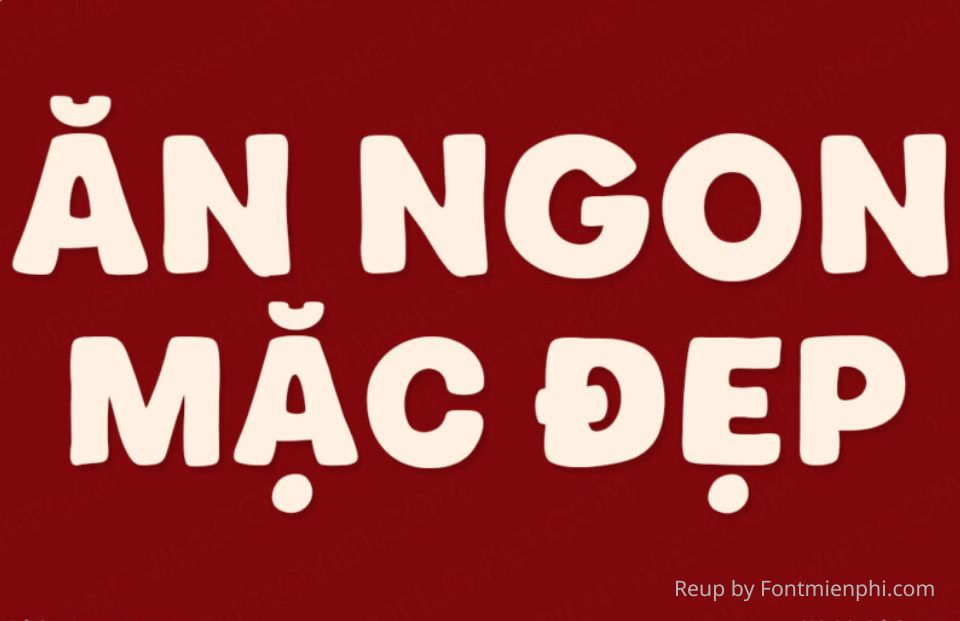
Font Việt hóa 1FTV VIP Boring Time – Kiểu chữ hoạt hình vui nhộn
1FTV VIP Boring Time là font chữ Việt hóa mang phong cách hoạt hình ngộ nghĩnh, nổi bật với những đường nét mềm mại, vui tươi và giàu tính sáng tạo. Font đặc biệt phù hợp với các thiết kế dành cho trẻ em, poster, banner, tiêu đề video, hình ảnh mạng xã hội, bao bì sản phẩm và nội dung giải trí.
Bộ font hỗ trợ chữ hoa, chữ thường, chữ số, dấu câu và hệ thống dấu tiếng Việt đầy đủ, giúp người dùng dễ dàng nhập nội dung tiếng Việt mà không gặp lỗi hiển thị. Font có thể sử dụng trên Windows, macOS và tương thích với nhiều phần mềm phổ biến như Photoshop, Illustrator, InDesign, Word và Canva.
Điểm nổi bật của font
• Phong cách cartoon đáng yêu, vui nhộn.
• Đã Việt hóa đầy đủ dấu tiếng Việt.
• Phù hợp làm tiêu đề, thumbnail và poster.
• Tạo điểm nhấn mạnh cho các thiết kế sáng tạo.